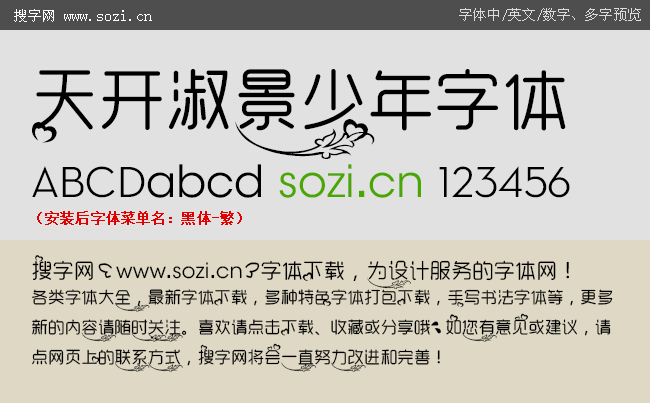
天開(kāi)淑景少年字體
搜字網(wǎng)給大家提供一款天開(kāi)淑景少年字體手機(jī)中文字體下載。這款手機(jī)字體是將悅圓體字體為原形,字體間嵌入漂亮的花紋圖案。造字工房悅圓常規(guī)字體為圓體字形,結(jié)構(gòu)秉承悅黑系列,筆畫(huà)風(fēng)格簡(jiǎn)潔,柔美優(yōu)雅。加入花紋后更添了一份趣味性,又保持了文字的識(shí)別度,特別適合喜歡手機(jī)字體個(gè)性一些的朋友在手機(jī)上安裝使用。